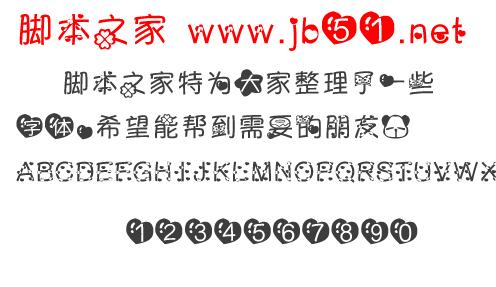
甜心童畫字體是一款非常漂亮的中文字體,該字體簡潔流暢,單純可愛,采用了非常所的圖案來點綴字體,整體效果十分的美觀和統(tǒng)一,字里行間也充滿了童趣,可以很好的應(yīng)用于文本裝潢、信息展示、網(wǎng)頁設(shè)計、篆刻制模、數(shù)據(jù)制作、裝潢設(shè)計、計算藝術(shù)設(shè)計、視覺設(shè)計、字帖等一切合法應(yīng)用場景,有喜歡的朋友可免費下載收藏。